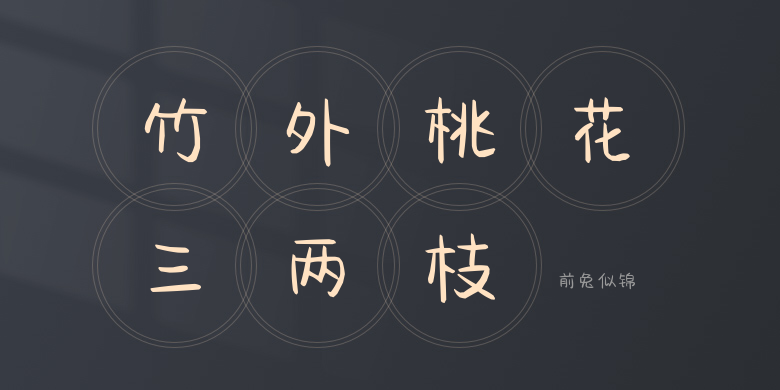
前兔似锦
前兔似锦,这款字体结构工整、笔画清晰,兼顾美观与易读性,适用于标题、正文、海报、包装、LOGO 等多种场景。字形优雅稳定,风格百搭耐看,适配日常排版与创意设计,让文字呈现更舒适、更具质感。前兔似锦一笔一画,皆是细节,以均衡的比例、流畅的线条打造舒适视觉体验,字形端正大气,风格简约现代。无论是商业设计、品牌宣传还是日常排版,都能轻松驾驭,让文字更有格调与力量。前兔似锦字体下载。